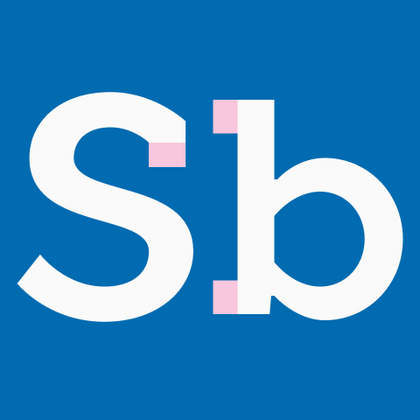
TT Rationalist is functional and neutral slab serif typeface.
TT Globs is the first font from the TypeType Starter Kit line.
TT Polls is the modern modular slab serif family for using in sports-related design.
TT Slabs. Slab serif, also called «square serif». They originate shortly after the Industrial Revolution (1850), when the advertising industry began to grow.
Брусковые шрифты
Основной особенностью брусковых шрифтов являются массивные засечки, которые могут быть прямоугольными, трапециевидными или скруглёнными. В отличие от антикв, они выделяются своей массивностью. На данный момент в библиотеке TypeType можно найти четыре разные брусковые гарнитуры, в каждой из которых создана для применения в определённой нише и направлена для решения конкретной задачи.
Кроме того, этой осенью у нас выйдет ещё одна нейтральная брусковая гарнитура, призванная закрыть нишу текстовой гарнитуры.
Но давайте по порядку. Самой первой брусковой гарнитурой в TypeType стал TT Slabs, который появился в 2014 году. Гарнитуру TT Slabs отличают геометрические формы знаков и засечек. Чуть позже, в 2015 году, мы выпустили узкую версию гарнитуры под названием TT Slabs Condensed, которая стала парой TT Slab и помогла расширить её функционал. Мы хотели, чтобы пользователь применял TT Slabs как шрифт для заголовков, подзаголовков, логотипов, а TT Slabs Condensed использовал для набора текстовых блоков или для экономии места на макете.
Вторым брусковым шрифтом, пополнившим нашу библиотеку, был TT Polls Slab. Он входил в состав более комплексного семейства TT Polls, которое состояло из очень эстетичного скрипта и слаба. Семейство TT Polls базировалось на исследовании Американской спортивной культуры и графики, что наложило отпечаток на визуальный облик обоих подсемейств. Отличительными особенностями TT Polls Slab является модульность, узость, и сквадраченность всех овалов. Особенно хорошо TT Polls Slab смотрится в сочетании с TT Polls Script.
Кроме того, в нашей коллекции есть сугубо дисплейный слаб TT Globs. В этом проекте мы создали очень современный дисплейный шрифт, заточенный на использование в большом размере кегля в постерах и афишах, в заголовках и подзаголовках, в логотипах и брендинге, и, конечно, в вебе. TT Globs — очень яркий и стильный шрифт, содержащий несколько интересных фич, благодаря которым можно сильно изменить его визуальное восприятие.
Ну и не забываем об экспериментальной вариативной гарнитуре TT Geekette, сочетающей дружелюбность в виде пластичных форм знаков и серьёзность, выраженную в моноширинности гарнитуры. Основной фишкой TT Geekette является вариативность, благодаря которой можно регулировать контрастность шрифта и выбирать между монолинеарным состоянием и ярко выраженным обратным контрастом. Кроме всего прочего, шрифт можно использовать в панели программирования или работать с кодом.
Осенью 2021 года наша библиотека пополнится ещё одним брусковым шрифтом, который будет отличать нейтральность и функциональность. Новый слаб будет заточен на работу в паре с нашими бестселлерами TT Norms, TT Commons и TT Hoves в качестве нейтрального текстового шрифта.